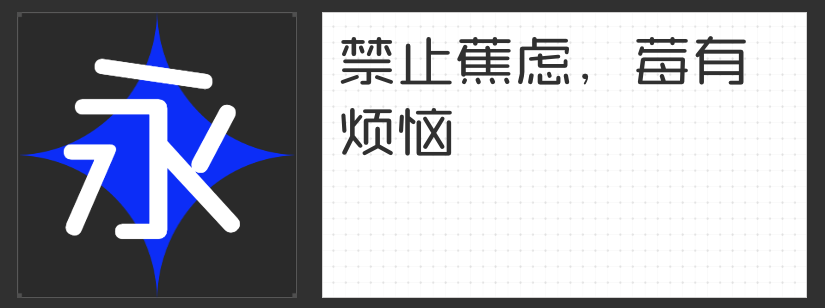
包装设计字体推荐:四款风格化字体解锁品牌视觉张力
在包装设计的视觉语言中,字体不仅是信息传递的载体,更是品牌性格的直观表达。一款契合产品调性的字体,能瞬间拉近与消费者的距离,强化记忆点。本文精选四款风格鲜明的字体,从柔和圆润到动态手写,从稳重屏显到节奏感设计,为包装注入独特灵魂。
一、励字圆梦简 常规
这款字体以“外圆内方”为设计哲学,将直线笔画与圆弧转折巧妙融合。竖折笔替代传统弧线,既保留了手写的自然感,又通过中宫松散的结构营造出呼吸感。其柔和的视觉语言尤其适合食品、日化等生活类包装,传递温暖、安心的品牌调性。圆弧起笔与收笔的设计,让文字在简洁中不失亲和力,成为提升产品亲切感的秘密武器。
二、字恋狂风摇简 常规
突破常规字体的静态平衡,这款字体以“被风吹过的手写感”为灵感,通过夸张的笔画倾斜与比例失衡,营造出摇曳生姿的视觉动态。歪扭的笔画与不规则的布白,赋予包装活泼俏皮的气质,尤其适合儿童产品、文创礼品或年轻化品牌。其手写温度与意外感,能在货架中迅速抓住消费者目光,传递“不按常理出牌”的品牌态度。
三、励字志向黑简 常规
融合圆体与黑体的双重基因,这款字体以圆角拐角打破传统黑体的生硬感,在稳重中注入一丝灵动。字面充实、结构紧凑的设计,确保了小字号下的清晰可读性,同时适配屏幕显示与印刷场景。其现代感与专业性,使其成为科技产品、高端食品或商务礼盒包装的理想选择,平衡了品牌调性与功能需求。
四、字恋狂漫野 摇风
以直线笔画为骨架,这款字体通过“断开”笔画与去钩处理,创造出通透的布白空间。大小错落的字型排列与灰度均匀的笔画设计,赋予文字音乐般的节奏感,适合追求艺术感的包装设计,如精品咖啡、手作饰品或独立出版物。其手写质感与抽象美感,能为产品披上一层“限量感”外衣,提升附加值。
包装设计中的字体选择,本质是品牌与消费者的一次视觉对话。这四款字体通过形态、节奏与情感的差异化表达,为产品赋予了独特的视觉基因。无论是追求治愈感、动态趣味、专业稳重还是艺术张力,都能找到契合的设计解决方案,让包装成为品牌故事的最佳讲述者。